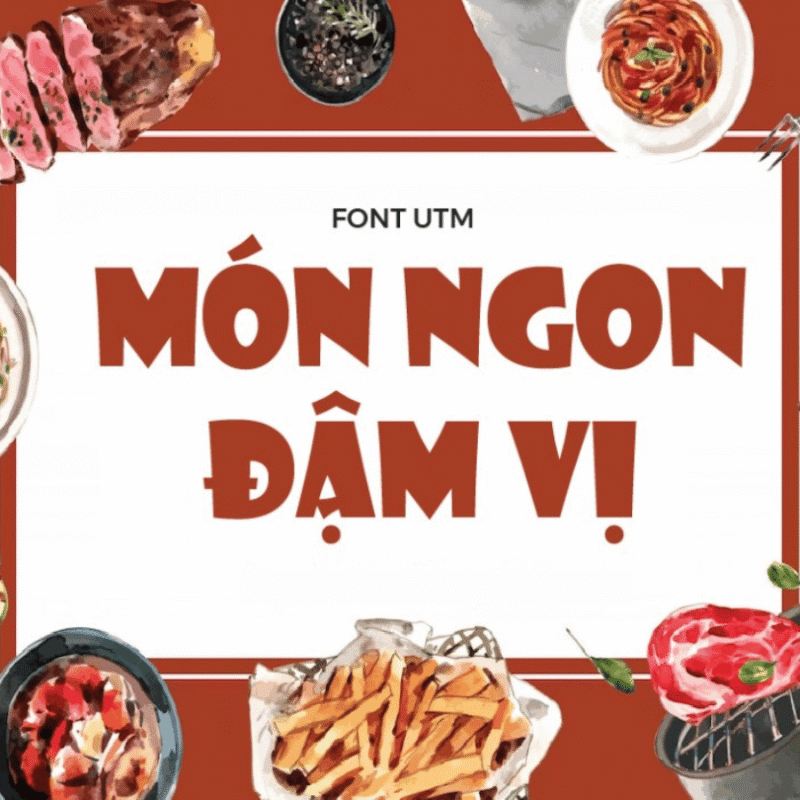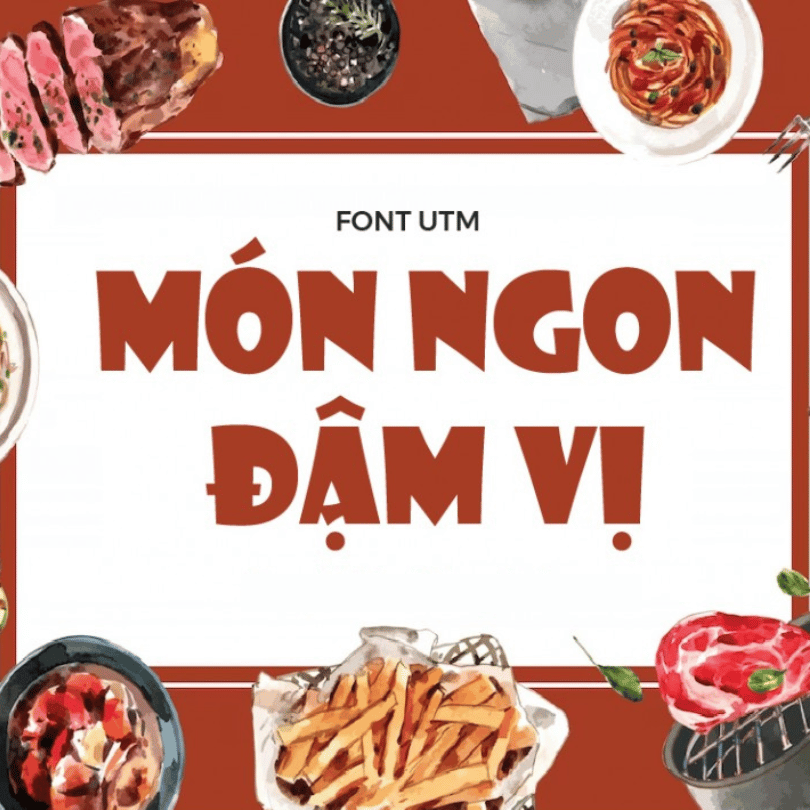
Việt hóa font UTM Showcard
Thông tin về font UTM Showcard
• UTM Showcard là một font chữ display (trang trí) có phong cách in đậm, góc cạnh, thường dùng cho tiêu đề, poster, thiết kế nổi bật.
• Font này thuộc bộ sưu tập của UTM (Urw Type Foundry) và có sẵn dạng free hoặc premium tùy phiên bản.